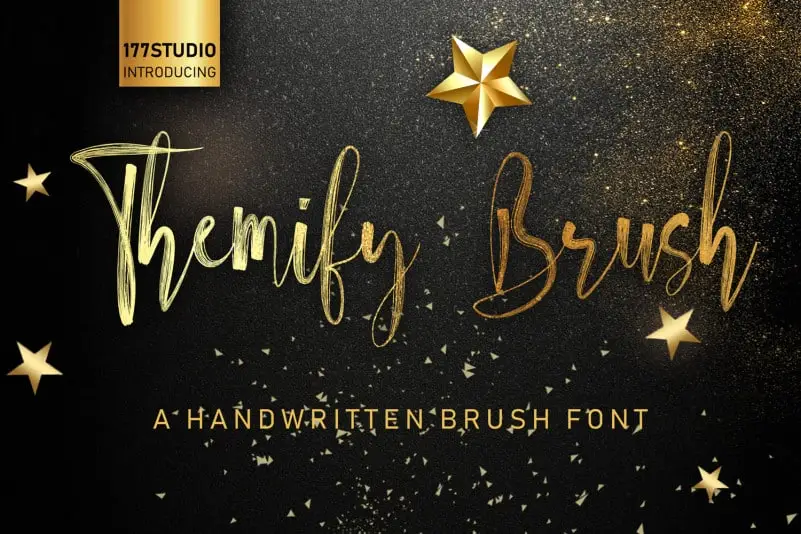
Themify Brush Font – Download Grátis
Introduzimos a Themify Brush Font para aqueles que buscam uma fonte script à mão escrita com personalidade forte. Esta fonte é perfeitamente adequada para projetos de marca, designs de mobiliário e embalagens de produtos. Suas expressões rústicas e seu estilo único garantem um toque autêntico a qualquer projeto. Seja em uma overlay de texto elegante sobre uma imagem de fundo ou como a base de qualquer design, esta font é ideal para quem busca um toque sofisticado e descontraído. É uma opção perfeita para designers gráficos que buscam adicionar um toque único aos seus projetos digitais. Escolha Themify Brush Font quando desejar criar algo realista e pessoal em seu próximo projeto.